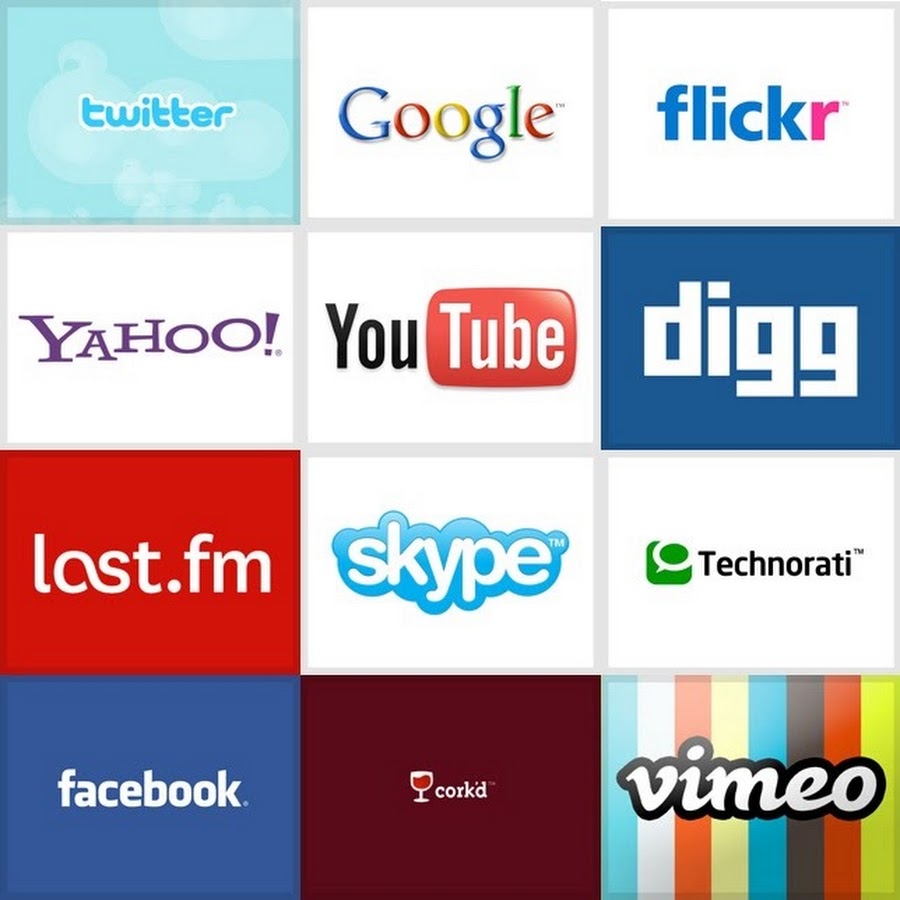
шрифты за самыми известными логотипами – Сей-Хай
Подумайте об известных шрифтах. В голову вам сразу придут Helvetica, Futura или, скажем, Comic Sans. Но кто-нибудь знает, какой шрифт использует Facebook? Да, мы тоже не знали.
Невозможно спрогнозировать, насколько успех вашего бренда зависит от шрифта. Но у всех брендов, перечисленных ниже, есть две общие черты: шрифты в их лого работают очень хорошо, и все они являются чрезвычайно успешными компаниями.
01. eBay
eBay использует Univers 53 Extended. С тех пор как сайт аукциона начал работу в 1995 году, у него было два совершенно разных логотипа. Первый был абсолютно дурацким. Тем не менее, потребовалось целых 17 лет, чтобы его поменять. Он сохранил цветовую гамму телевидения для детей, но буквы теперь не наезжают друг на друга.
Они теперь выстраиваются в линию, поэтому Univers 53 Extended выглядит намного умнее и взрослее, чем в предыдущем логотипе. Univers был разработан Адрианом Фрутигером еще в 1960-х годах.
02. FedEx
Шрифт в логотипе FedEx представляет собой комбинацию Futura Bold с небольшим количеством Univers 67. Кроме того, отдельно стоит отметить негативное пространство между «e» и «x». Это говорит нам о том, как компания видит себя. Шрифт выбрали точно так же.
Futura, разработанный Полом Реннером, основан на геометрических формах и существует с 1920-х годов. Он сильный и надежный; от него веет компанией, которая почти никогда не теряет вашу посылку.
03. Twitter
В последние годы Twitter отошел от своего логотипа, предпочитая использовать логотип птицы сам по себе. А используемый шрифт называется
Twitter в первые дни выглядел новым, странным и игривым. Так что шрифт действительно отражает это ощущение.
Логотип птицы сам по себе выглядит намного сложнее, но ему определенно не хватает игривости оригинального лого.
04. Facebook
До 2014 года в Facebook использовалась измененная версия Klavika, разработанная Джо Кралом десять лет назад. Нынешний логотип ушел недалеко от оригинала – его лишь сделали «более дружелюбным и доступным». Официально, шрифт в новом лого не имеет названия – Эрик Олсон из Process Type Foundry разработал ин-хауз.
05. Amazon
Текущий логотип Amazon существует с 2000 года. Новый шрифт – модифицированная версия Officina Sans Bold от Эрика Шпикермана. Дизайнер Энтони Байлс слегка изменил надписи и добавил оранжевую стрелку, похожую на улыбку. Эта «улыбка» теперь мгновенно узнаваема. И все это выглядит довольно свежо.
06. Apple
Многие известные ролики Apple использовали нестандартный вариант шрифта ITC Garamond под названием Apple Garamond. С 2002 года компания начала использовать семейство шрифтов Myriad, которые Роберт Слимбах и Кэрол Твомбли разработали для Adobe.
В 2017 году Apple перевела большую часть текста на своем сайте в San Francisco. Он явно вдохновлен Helvetica и DIN, поэтому компания ограничивает его использование. Сторонние разработчики могут использовать его только для платформ Apple.
07. Microsoft
До 2002 года Microsoft использовала шрифт Helvetica Black Oblique. Текущий логотип – четырехцветная плитка – был представлен в 2012 году. В логотипе используется Segoe, разработанный Стивом Маттесоном из Agfa Monotype.
Microsoft теперь использует Segoe в качестве основного фирменного шрифта для рекламных и печатных материалов и подсемейство Segoe UI для одинакового визуального эффекта на экранах и в печати.
08. Disney
История гласит, что шрифт, используемый для лого Disney, основан на почерке Уолта Диснея. Но копии его писем показывают, что это далеко не так – в лого просто используется стилизованная каллиграфия.
В 2000 году Джастин Каллаган выпустил бесплатный программный шрифт Waltograph на основе леттеринга компании.
Это неофициальный проект, но представители Disney отметили его. «Когда Микки Маус садится за написание мемуаров, мы уверены, что шрифтом он выбрал именно Waltograph».
Все самые популярные бренды имеют две общие черты: шрифты, используемые в их логотипах, очень хорошо работают, и все они являются успешными компаниями уже десятки лет. Поэтому мы решили сделать подборку топ-10 популярных шрифтов, которые помогут вам создать логотип, который будет оставаться актуальным ближайшие 100 лет. Эти шрифты подойдут не только для логотипов, но и для любого вашего дизайна.
Топ-10 шрифтов, которые вы будете видеть еще долго
1. Helvetica
Год создания: 1957
Автор / Дизайнер: Max Miedinger, Monotype Studio
Страна: Швейцария
Стиль: Нео-гротеск (без засечек)
Шрифты для логотипов делятся на два типа — Helvetica и все остальные.
И это абсолютная правда. McDonalds, Nestle, Toyota, Jeep, BMW, LG, NBA, Panasonic, WhatsApp, Microsoft, Oral-B, Skype — все они созданы на основе одного шрифта — Helvetica, и это далеко не полный список.
Среди продуктов, продаваемых по всему миру, это один шрифт и бренд, которому вы можете доверять!
Поиск шрифта, соответствующего вашему бренду
Увидев некоторые из самых узнаваемых шрифтов, вы, вероятно, задаетесь вопросом, каким может быть ваш фирменный шрифт. В отличие от школьного обучения в 90-х, где комикс был предпочтительным шрифтом для проектов, который подрывал требования вашего учителя к Times New Roman, выбор шрифта, который сделает акцент на вашем бренде, может быть проблемой.![]()